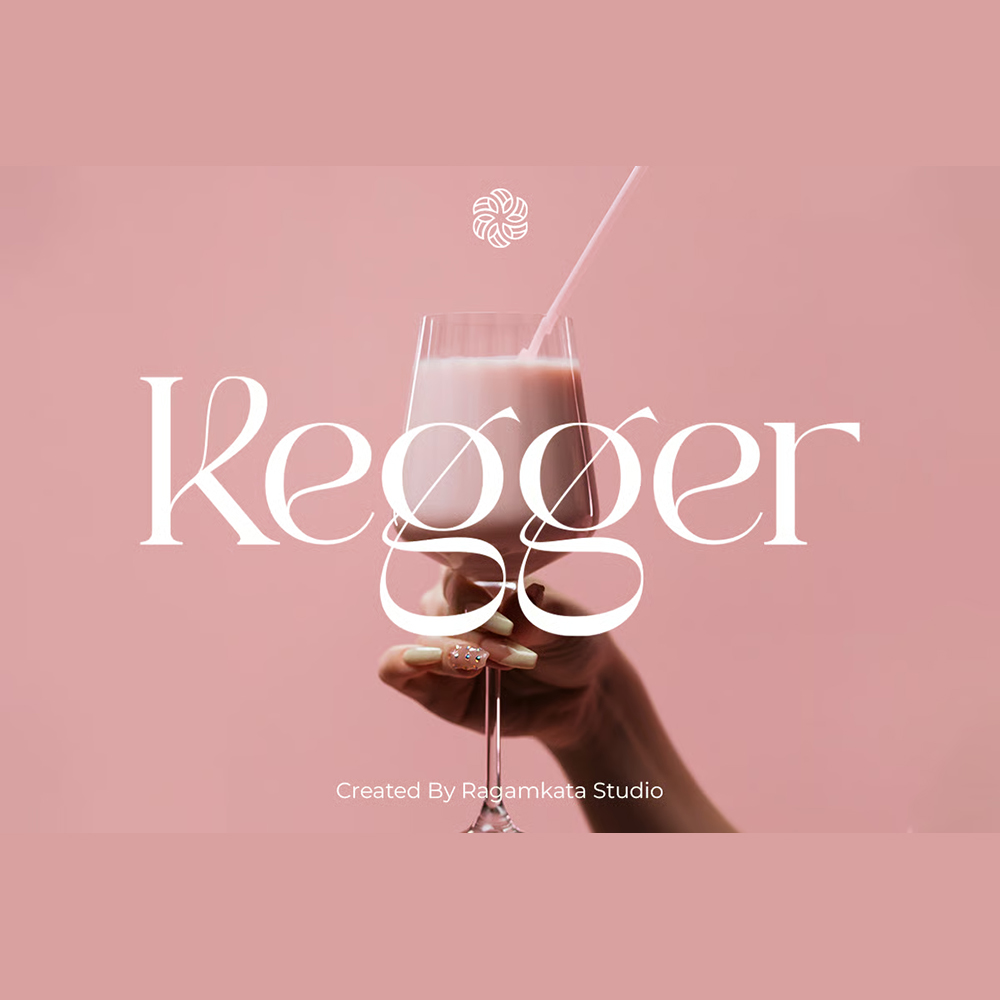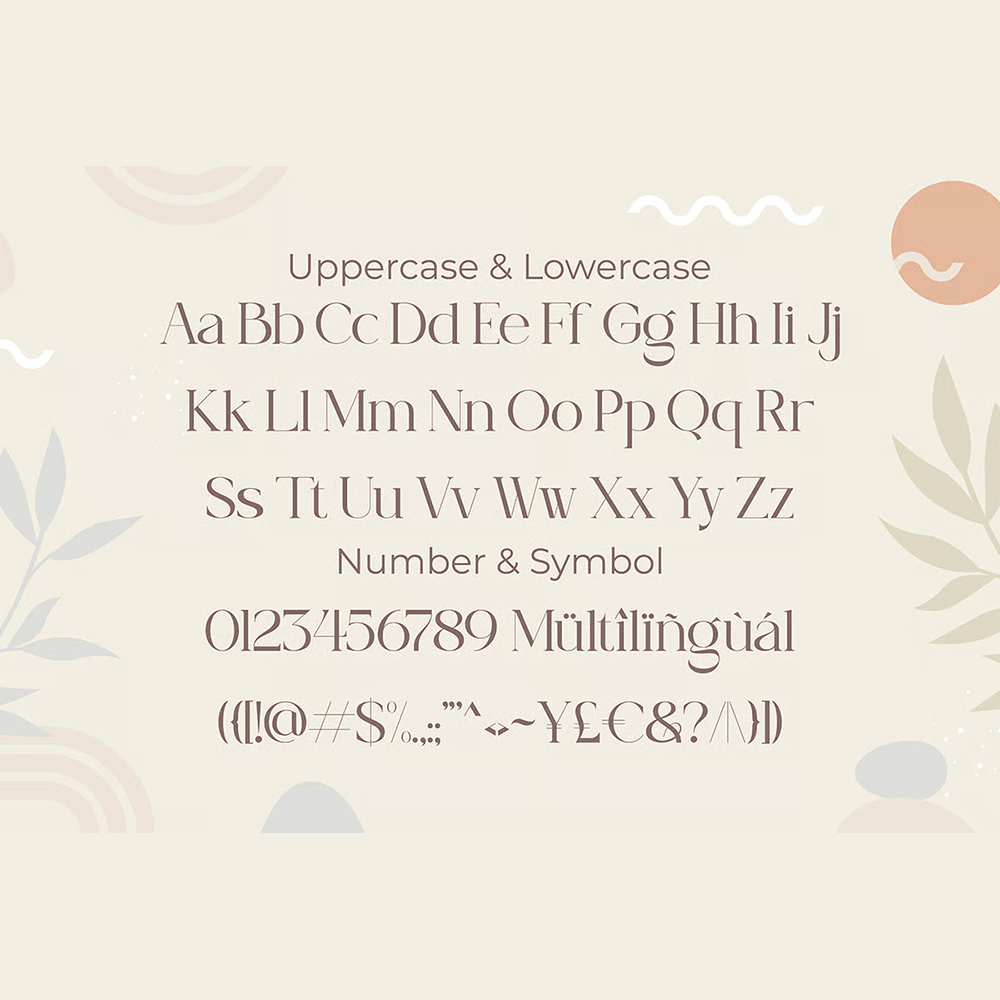
فونت پرمیوم و انگلیسی Kegger Font یک فونت نمایشی زیبا با کاراکترهای بزرگ و پررنگ با جزئیات تزئینی منحصر به فرد روی هر کاراکتر است. این فونت در عین حال که مدرن و مطابق با روندهای طراحی فعلی است، حس زیبایی و کلاسیکی را القا میکند.Kegger برای پروژههای متنوعی که نیاز به ظاهری لوکس و چشمنواز دارند، مانند کارتهای دعوت عروسی، طراحی بستهبندی محصولات لوکس یا مواد تبلیغاتی برای برندهایی که به دنبال انتقال تصویری منحصر به فرد و لوکس هستند، ایدهآل است. این فونت سریف همچنین برای طراحی لوگو یا وبسایتهایی که هدفشان نمایش ظاهری خلاقانه و زیبا در عین حفظ ظاهر حرفهای و کلاسیک است، مناسب است.
مزایای استفاده از فونت لاتین Kegger Ballerina چیست؟